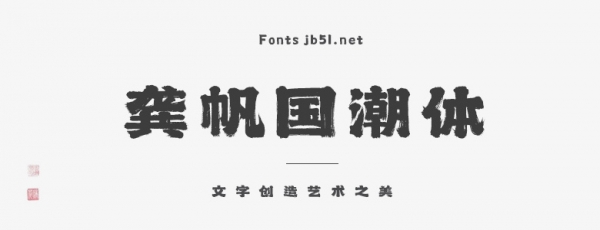
龔帆國(guó)潮體,是傳統(tǒng)漢字文化與現(xiàn)代藝術(shù)相結(jié)合打造的一款字體,新元素國(guó)潮是此套字庫(kù)的亮點(diǎn),適用于搭配標(biāo)志、廣告標(biāo)語(yǔ)、商業(yè)廣告、包裝、影視、游戲動(dòng)漫等廣泛應(yīng)用領(lǐng)域。